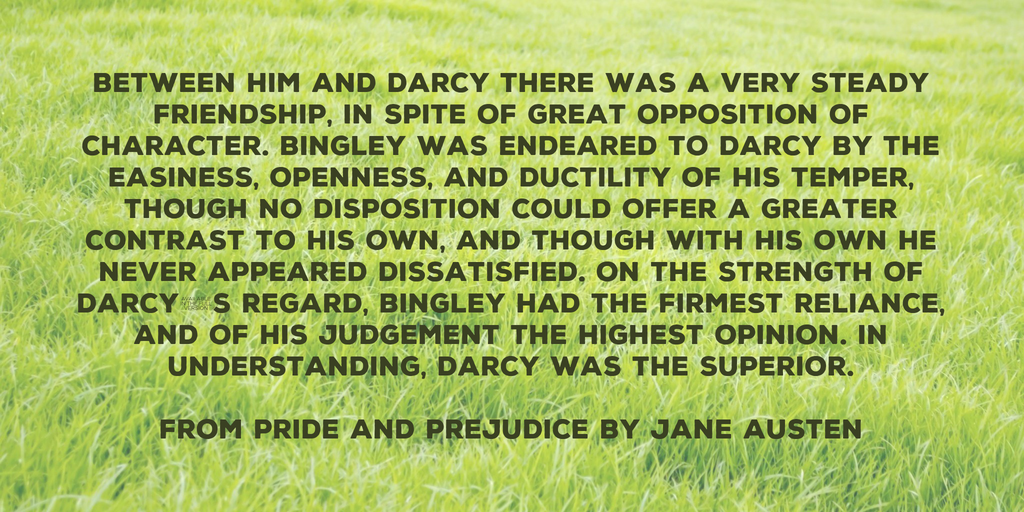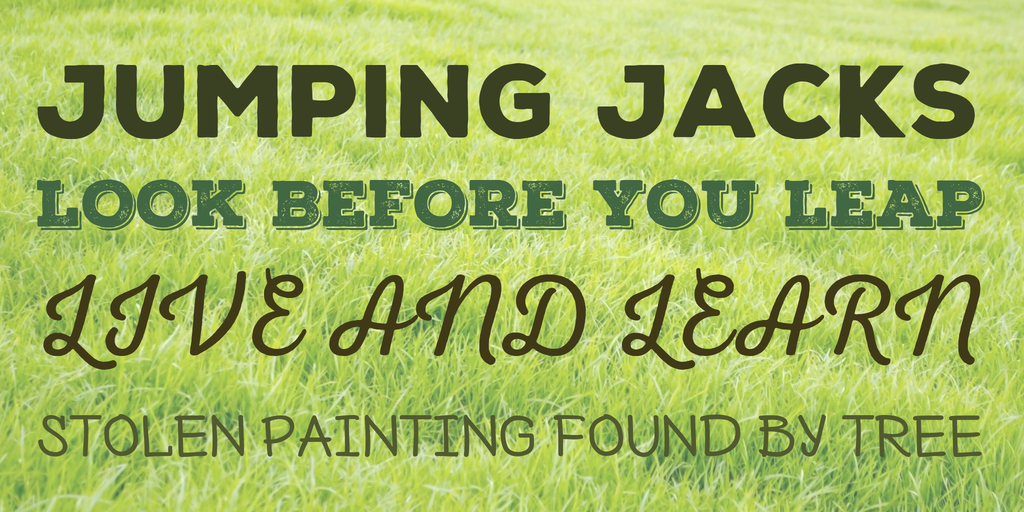
Nexa Rust Font Ailesi font
Fontfabric Type Foundry'den Nexa Rust, yazı tipi alt aileler Sans, Döşeme, Komut, El Yapımı ve Ekstralar'dan oluşan çok yönlü bir yazı tipi sistemidir. Bu alt ailelerin her biri karakteristik sıcak, kaba bir görünüme sahip ve Birkaç doygunluk derecesi.